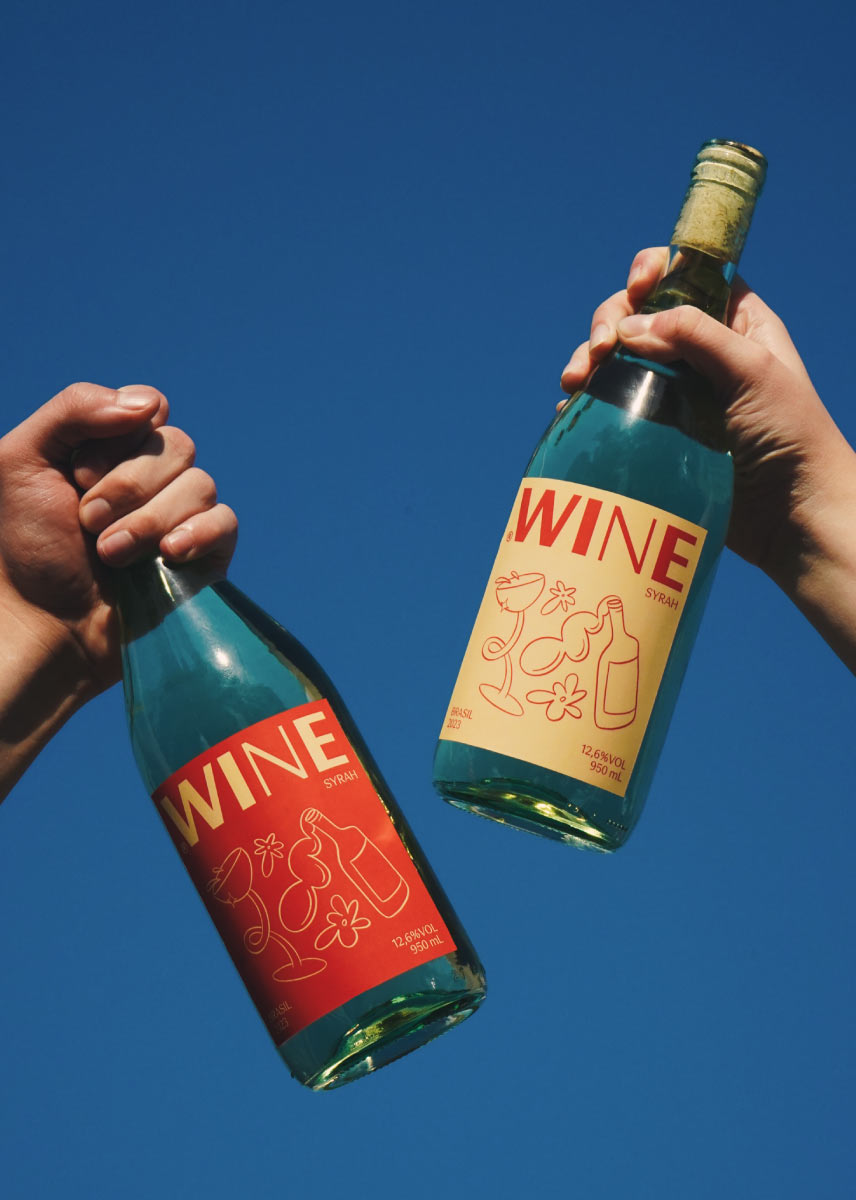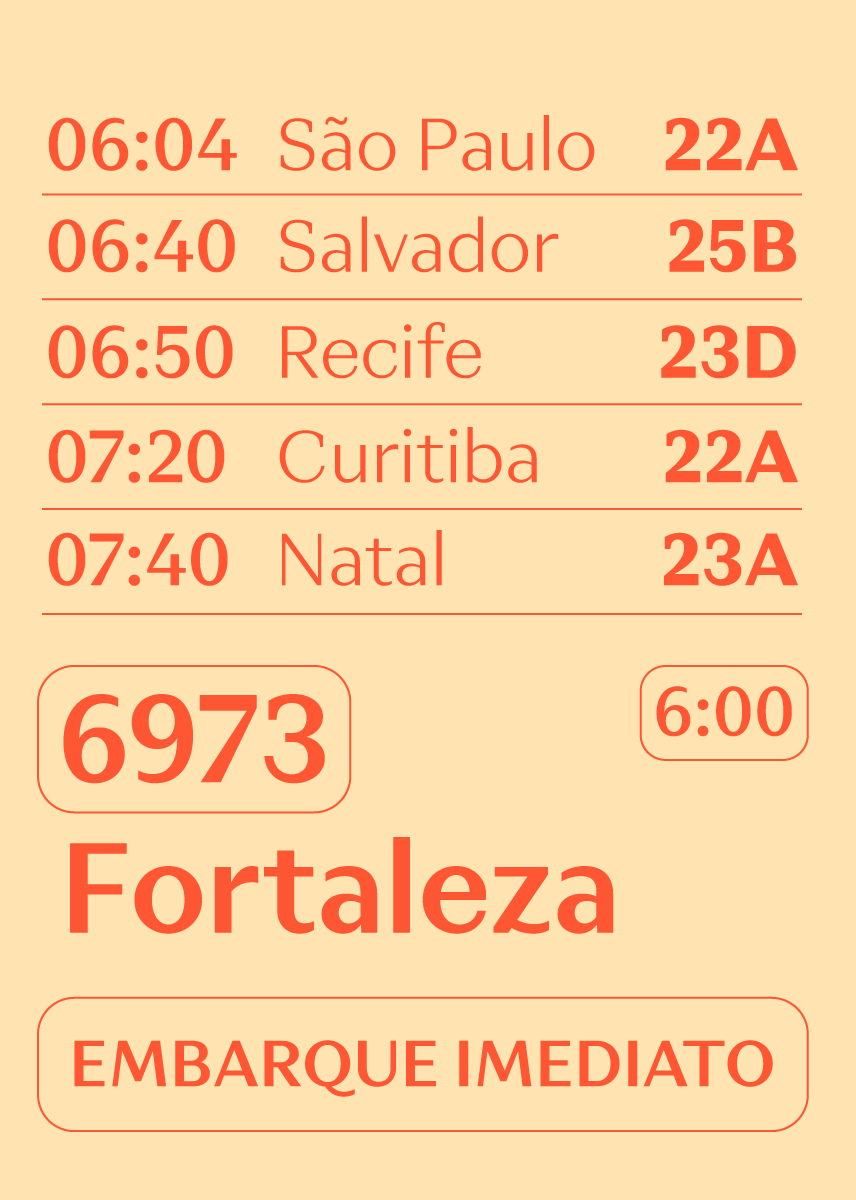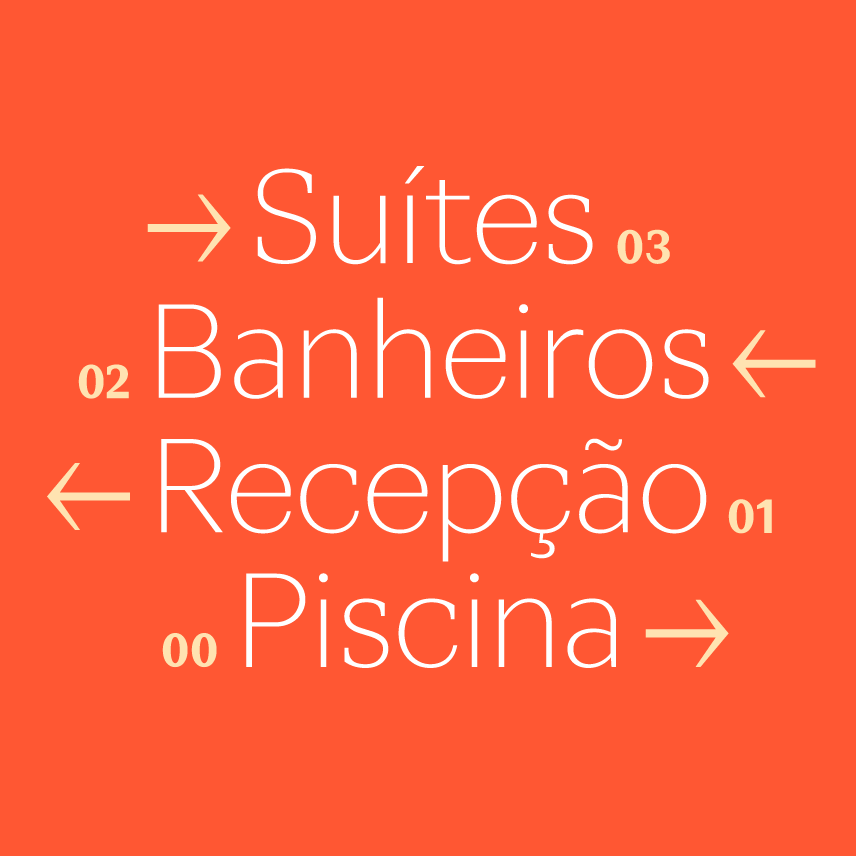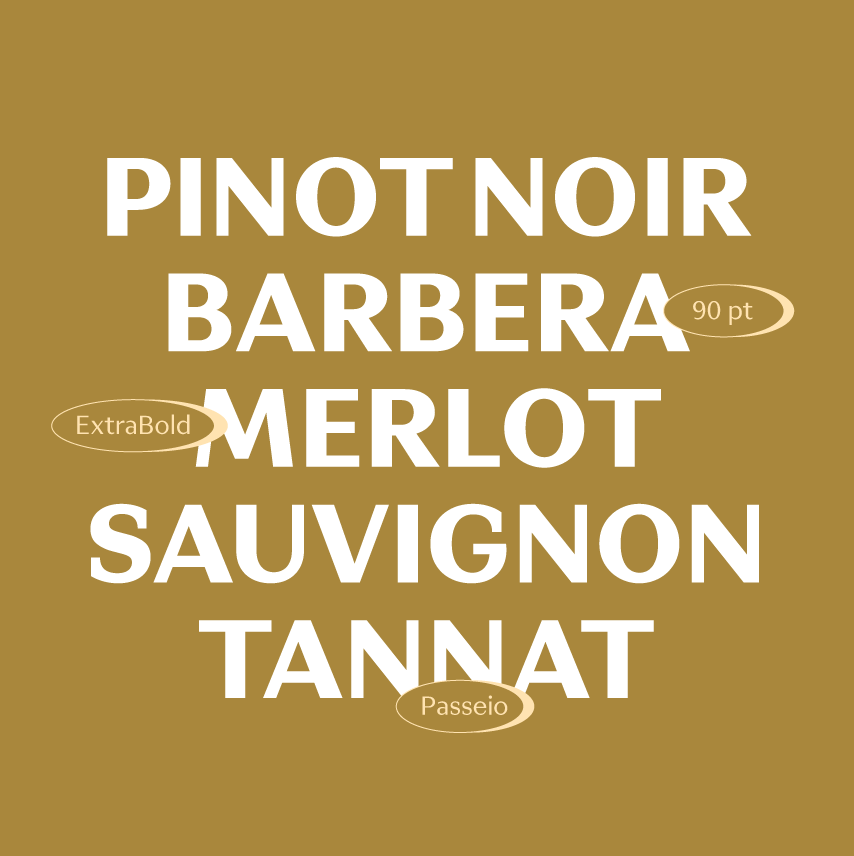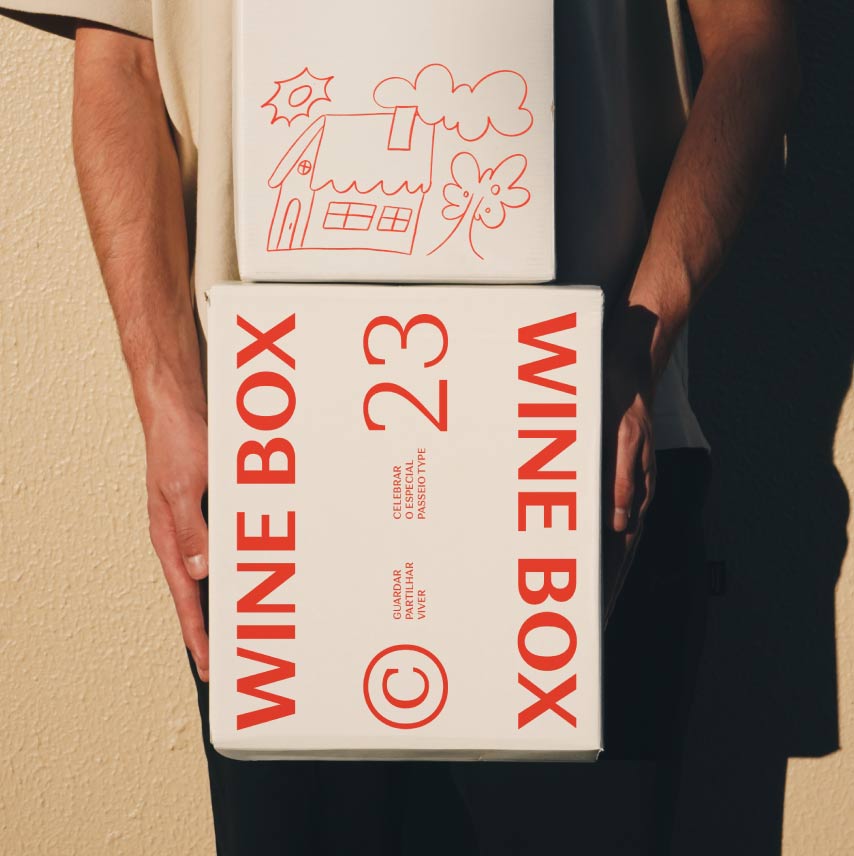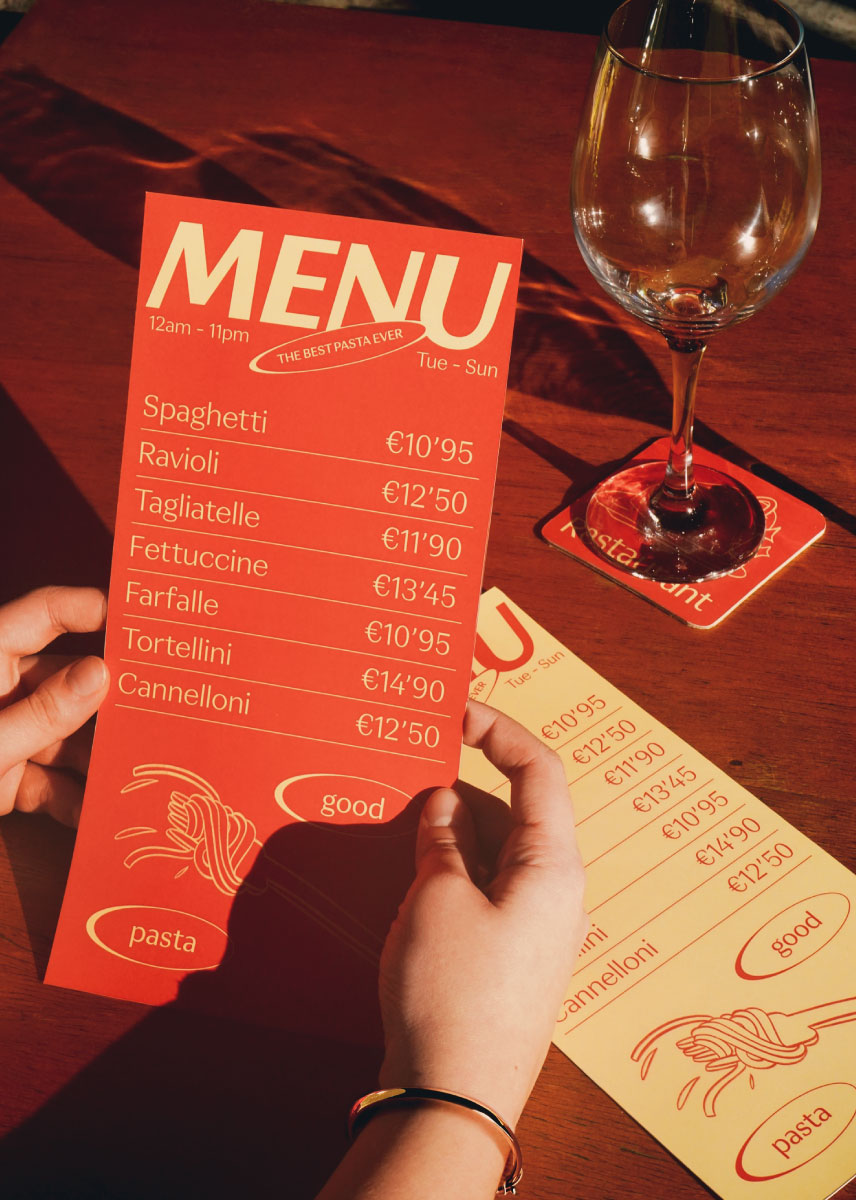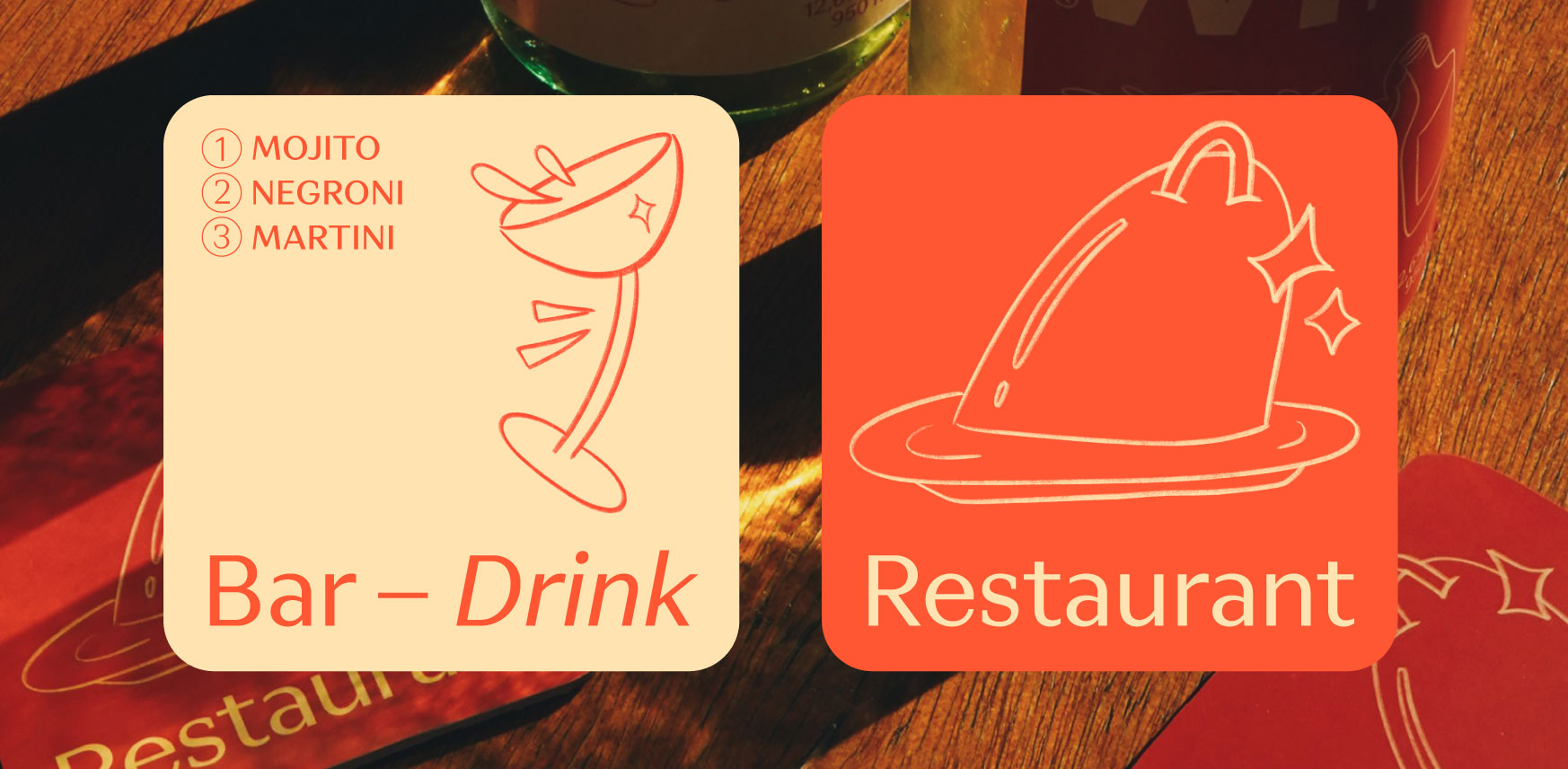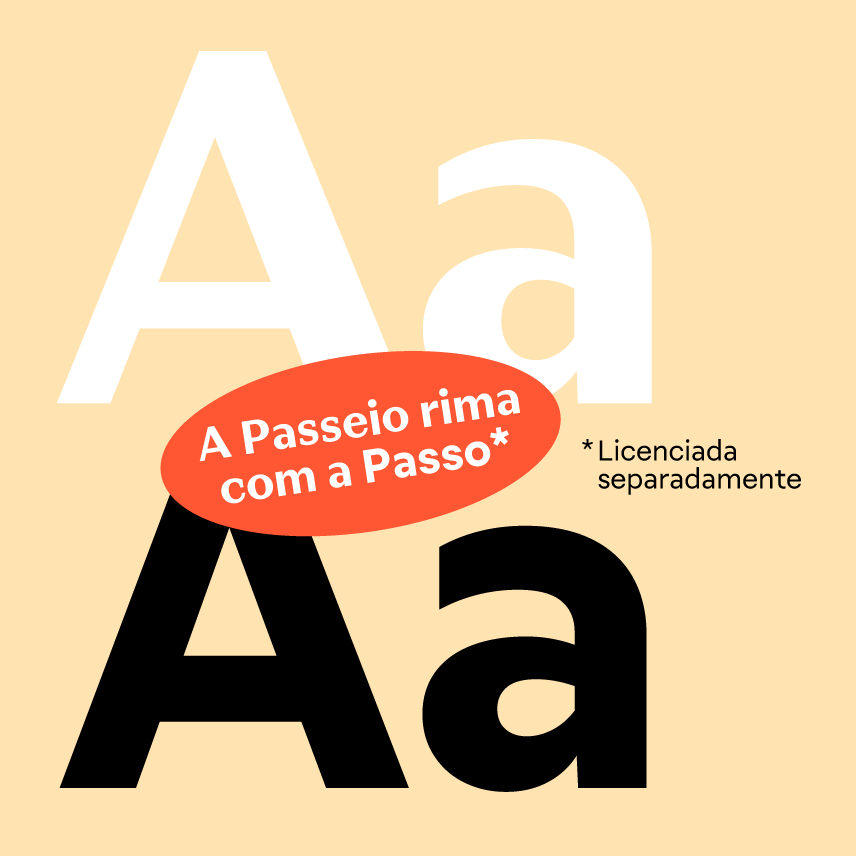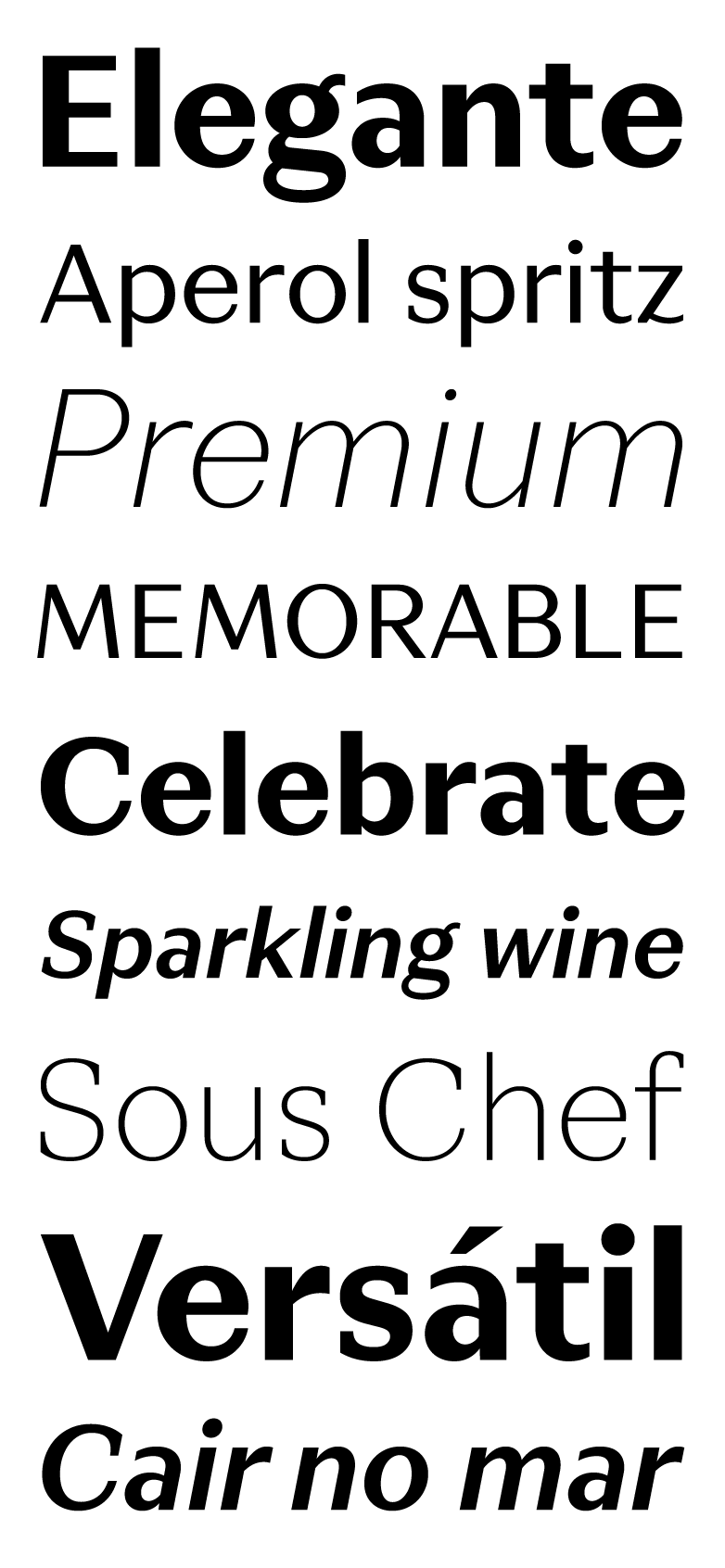
O suave respirar na meditação em silêncio. Galáxias se expandindo no universo. Folhas crescendo no apartamento. Uma coisa conecta tudo isso: estar vivo é estar em movimento.
No dia a dia aceleramos o passo. Rotina, forma seguindo a função. De olho no passeio do final de semana. Ou melhor, desta tarde? Por que não?
Foi pensando nos diferentes ritmos da vida que criamos as tipografias Passo e Passeio, lideradas pela Ana Laydner. Com um pé na frente do outro, de passo em passo, vamos desenhando e vivendo.
A Passo tem a constância da rotina. Monolinear, com baixo contraste, ela entrega a mensagem de forma eficiente e direta. É o cafezinho para repetir a qualquer hora do dia. Vai te ajudar a resolver vários desafios sem levantar questões existenciais. Já a Passeio carrega as nuances de um alto contraste e algumas terminações serifadas. É elegante e vai tomar a sua atenção. Te convidar para sair ou cair no mar. Abrir um espumante. Sair para viajar. A parar e celebrar.
São desenhos opostos mas não antagônicos: compartilham da mesma construção e métricas verticais, ou seja, podem ser combinadas e misturadas pra refletir a montanha-russa que é a vida.
Acelerar o passo ou diminuir para passear, há sempre uma hora e um lugar.